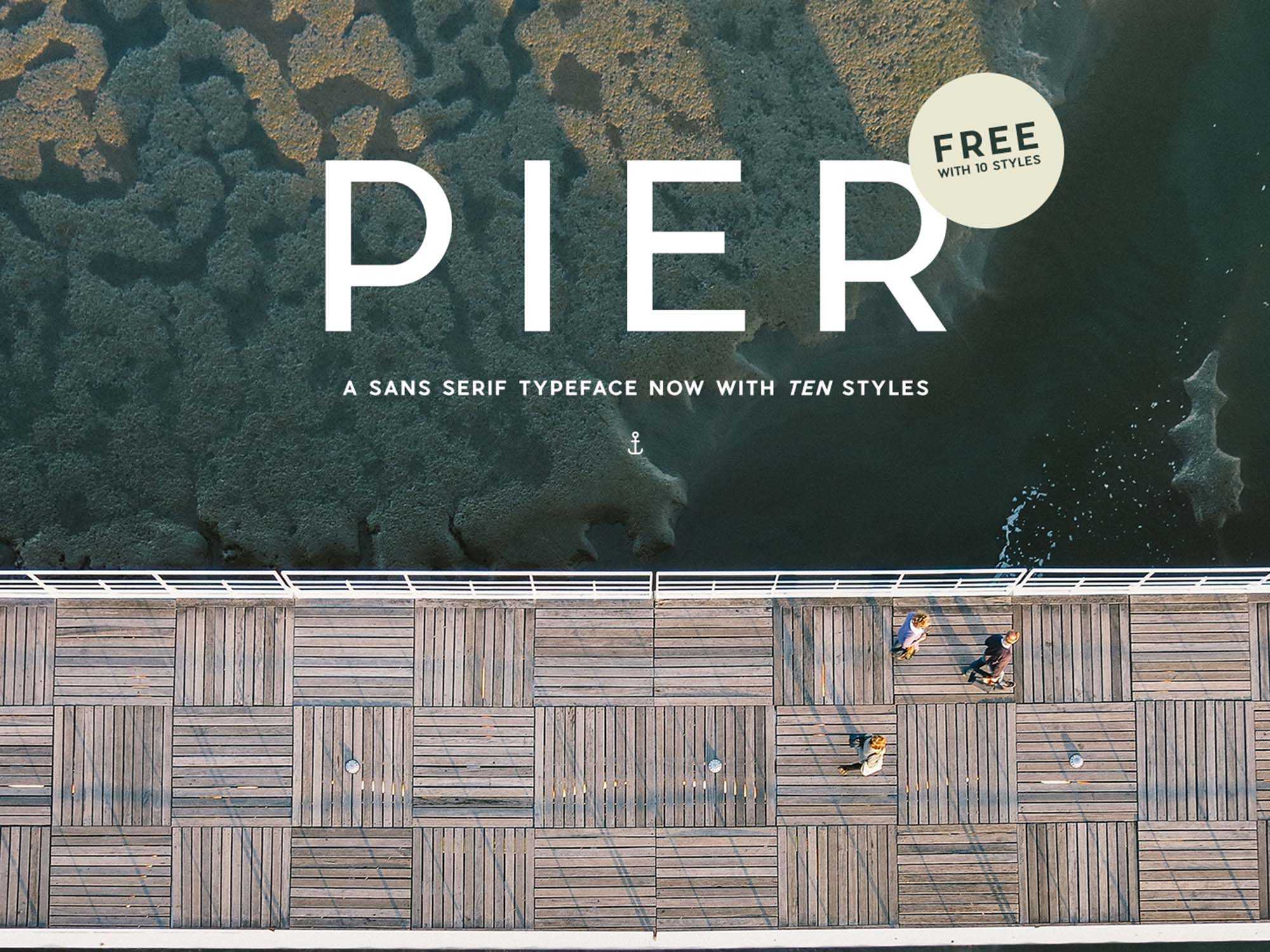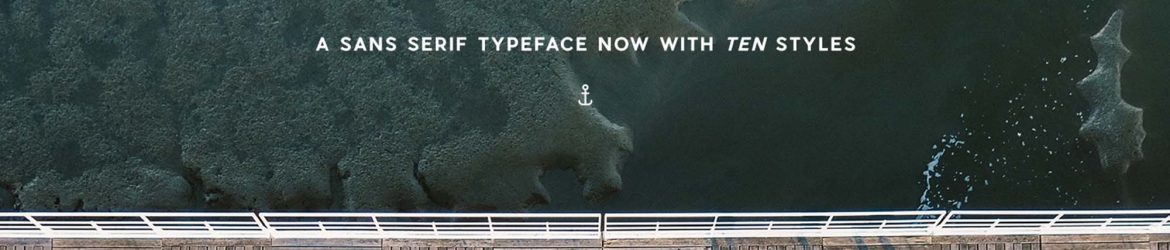
Pier Sans Font Family – Download Grátis
Pier Sans é uma famosa sans serif moderna e bem estruturada que traz uma nova perspectiva à tipografia. Seu conceito é criar um tipo de fonte geométrica ligeiramente desviada que se adapta a qualquer tamanho – grande ou pequeno. Através de sua utilização, você pode destacar os pontos-chave de seus projetos. Este tipo de fonte consegue se encaixar em qualquer projeto de design que você possa imaginar, de websites e revistas a impressões em grande escala. Pier Sans é uma escolha atraente para quem busca uma estética minimalista e sofisticada, perfeitamente adaptada a um amplo espectro de aplicações gráficas. Que tal explorar mais esta incrível opção de tipo?